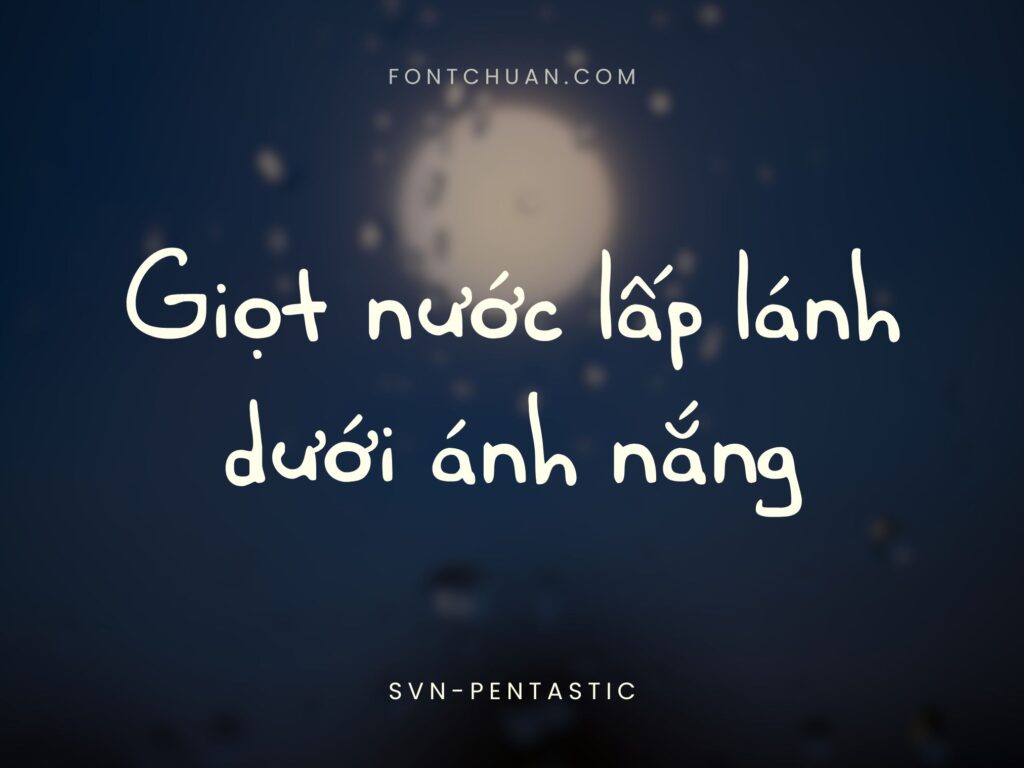
Font SVN Pentastic Việt Hóa
Tác giả Font: Natsuko Hayashida
Font SVN Pentastic là phiên bản Việt hóa của kiểu chữ Pentastic, được thực hiện bởi STYLEno.1 Fonts. Pentastic là một kiểu chữ viết tay mang phong cách tự nhiên và thanh lịch, được thiết kế bởi Natsuko Hayashida. Font này nổi bật với các nét chữ mềm mại, uyển chuyển, tạo cảm giác thân thiện và gần gũi. Pentastic bao gồm đầy đủ các ký tự chữ hoa, chữ thường, chữ số và dấu câu, hỗ trợ đa ngôn ngữ. Font này phù hợp cho nhiều mục đích sử dụng khác nhau như thiết kế thiệp mời, logo, tiêu đề, bao bì sản phẩm và các ấn phẩm truyền thông.
SVN Pentastic lý tưởng cho các dự án thiết kế yêu cầu sự tự nhiên và thanh lịch, như thiệp cưới, thiệp mời sự kiện, logo thương hiệu và các ấn phẩm truyền thông. Các ngành nghề như thiệp cưới, giáo dục và bất động sản có thể tận dụng font này để tạo điểm nhấn trong thiết kế. Ngoài ra, font cũng thích hợp cho các sự kiện như Tết, Valentine, Sinh nhật và các lễ hội khác.